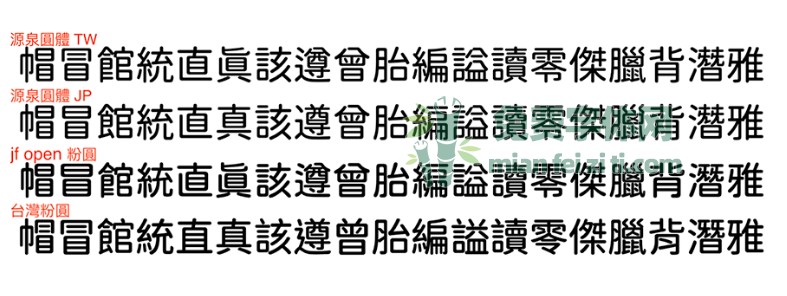
台湾粉圆体:Jf open粉圆与思源黑体改造字合体字形
台湾设计Max又修改了一个字体,一开始是想把jf open 粉圆 字体里“肉”、“纟”、“女”、“辶”、“食”的笔顺换成中国台湾教育部建议的写法。
大约修改了几天就完成了,一天可以调整一个部首。后来想说都改了,顺便来调整一些小细节吧,于是就从“厶”符号开始,这个日系的写法很特别,横线左边会特地留下一小段的空白,最后越改越多……。
感触最大的是思源黑体与jf open 粉圆的字腔大小不一样。粉圆较大,思源字腔较小,外放内收的结构在轮廓上看起来较有腰身,和传统汉字书法所讲究的美感相近,版面留白较多一点,较透气些。这个满神奇的,微调一下字的组成元件的位置或距离,文字传达出不一样的感觉,而且差异很显著。那些写字漂亮的人,真的很厉害!
台湾粉圆体基于思源黑体与jf open 粉圆,大多的字是思源黑体为主,欧文还有部份的中文使用粉圆的中文字。